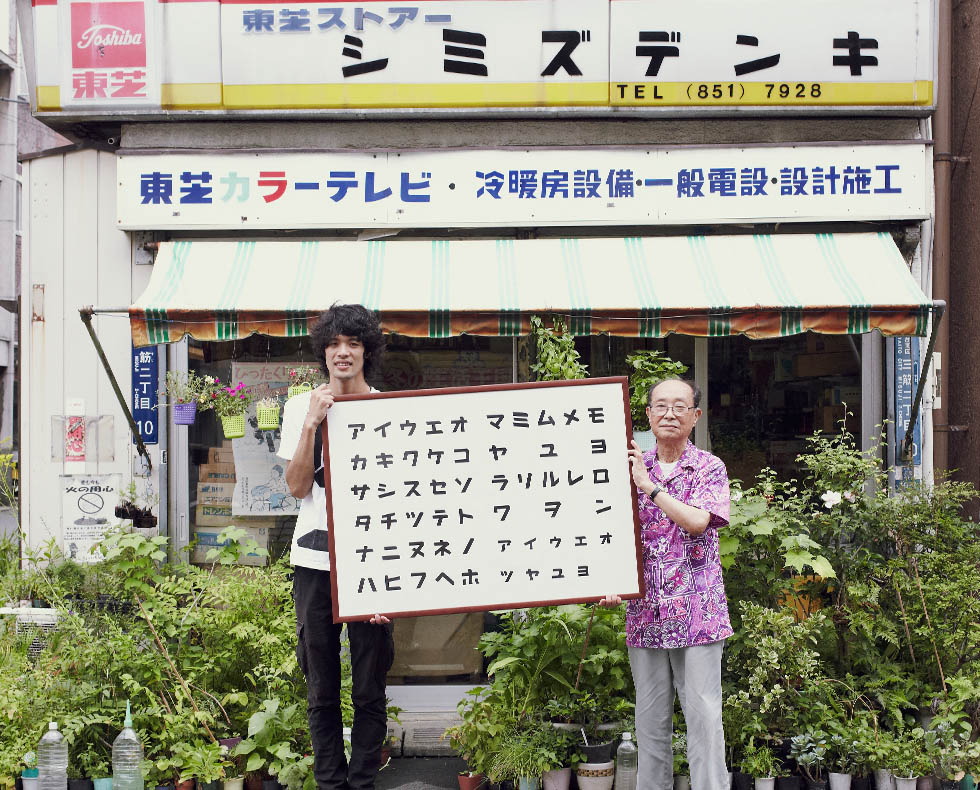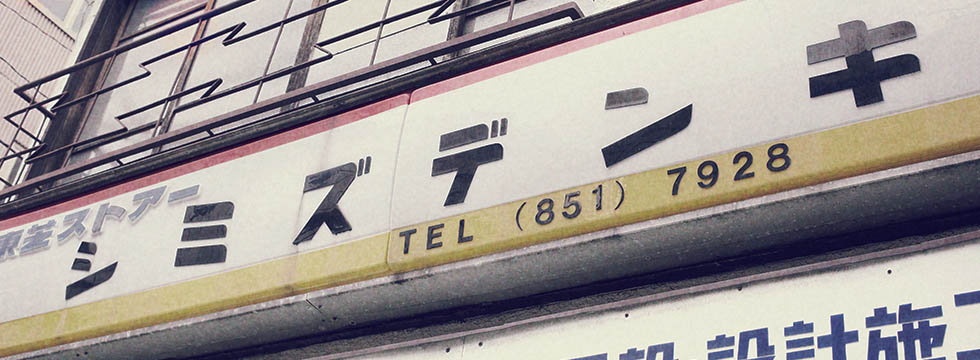
角張った部分と、丸い部分の連続が、リズムとなって網膜で踊る。文字のフォルムも動的で、心地よいスピード感が感じられる書体である。
「シミズデンキ」は、終戦直後に開業した電気店。当時はラジオを取り扱い始めた頃で、店の前にたくさんの人が集まり、ラジオ体操や相撲を実況を楽しんだそうだ。現在の店主、清水さんは二代目。松下電器主催のテレビの修理技術コンテストにおいて、台東区でトップの成績を収めたこともある。電気店らしい書体は開業した当時に看板屋にお願いして作ってからずっとこのまま。電気店としての営業は今はほとんどしていないそうだが、最近は近くの学校に協力して植物を育てる仕事をしているそう。電気屋さんとしての仕事を引退してもシミズデンキは、この書体とともにいつまでも残っていてほしい。
“Shimizu Denki” was an electronics shop that opened right after the end of World War II. That time is when the store started selling radios. Many people gathered in front of the shop to enjoy a broadcast such as radio calisthenics and live coverage of Sumo. The current owner, Mr. Shimizu, is the second generation. He once won the top prize in a TV repair skill contest sponsored by Matsushita Electric Company in Taito, Tokyo. The typeface that is typical of an electronics shop has remained the same since they asked a signboard shop to make it when they started the shop. He said that he rarely does business as an electronics shop now, but recently they have been working for a nearby school to grow plants. We hope that Shimizu Denki and its typeface will remain forever even after he retires from his business as an electrician.